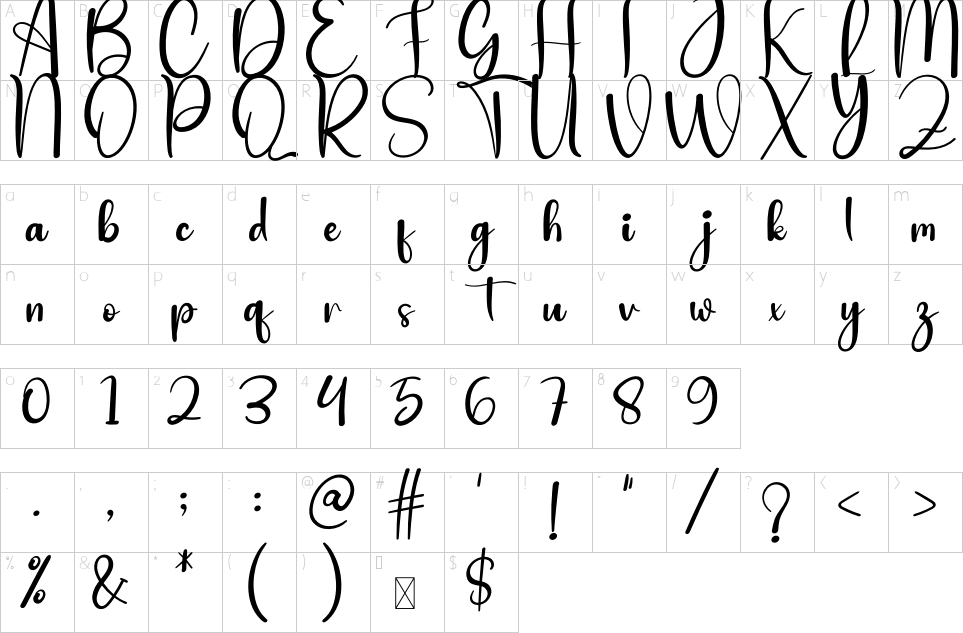
Descubra a fonte Pink House, ideal para criar designs frescos e modernos. Desenvolvida pelo designer William Jhordy, esta fonte é perfeita para quem busca uma elegância simples e sofisticada. Com 1.932 downloads, Pink House já ganhou o reconhecimento de muitos criadores de conteúdo. Seja para design de logotipos, criação de sites ou até mesmo para adicionar um toque único a suas mensagens de e-mail, Pink House é uma ótima escolha. Inspirado no movimento minimalista, sua forma arredondada e cores suaves fazem de Pink House uma fonte versátil e divertida para qualquer projeto. Sua elegância não se limita a um estilo único, mas se adapta bem às diversas aplicações, tornando-a um must-have para seu arsenal de fontes gratuitas. Download Pink House agora e deixe sua marca brilhar com a fonte certa.